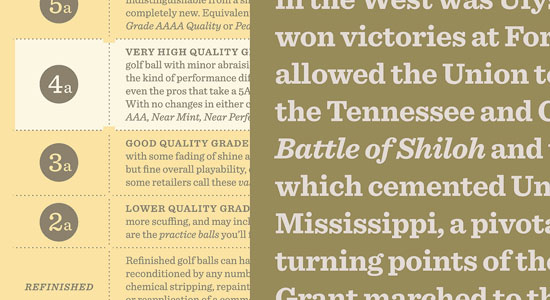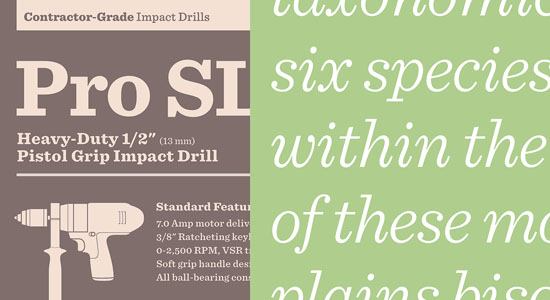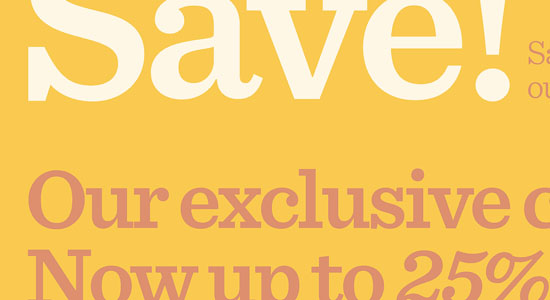
Sentinel (Hoefler & Frere-Jones)
For everyone who wishes Clarendons had italics, and everyone whose favorite slab serif is shy a few weights: Sentinel was designed for you.
The first slab serifs were designed to be oddities. It was their intention to be eye-catching, to be novelties amidst the world’s conventional book types. Never mind that some of these faces treated different letters inconsistently, or had inherent qualities that limited the size of their families: these were eccentricities, and to a novelty typeface, eccentricity is strength. Two centuries later, their legacy includes three beloved species of typeface that are handsome, popular, and maddeningly difficult to use. Each is marred by a crippling deficiency, a situation inspiring us to create Sentinel.
Hmm, wieder eine sehr gefällige Online-Präsentation der Schrift. Wieder einen Klassiker genommen und text-kompatibel ausgeformt, passt deshalb auch prächtig in die Reihe Times (Mercury) oder Century (Chronicle).
Reaktion 1: Nee, lieber dann die etwas launigeren Interpretationen diverser Vorlagen von Christian Schwartz, die nicht ganz so systematisch vom Stapel gelassen werden.
Reaktion 2: Ruhig Blut, das ist große, an heutige Bedürfnisse angepasste Schrift, die halt auf einem Klassiker beruht, an dem sich noch niemand sattgesehen hat. Was willst, erwartest du mehr?!
Nur mal zur Veranschaulichung: